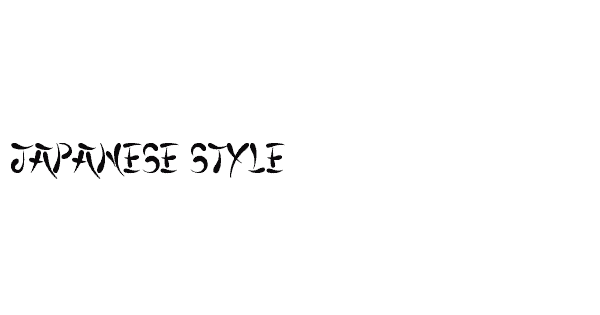
CD Projekt, использовавшая в прошлом году стереотипные азиатские шрифты в игровой графике, не ответила на запрос CNN о комментариях.
В 2020 году, когда пандемия Covid-19 открыла новую волну синофобии, канадский бренд одежды Lululemon уволил своего арт-директора после того, как он, по-видимому, одобрил дизайн футболки «Bat Fried Rice» со словами «Нет, спасибо», опубликовав это в его Instagram.